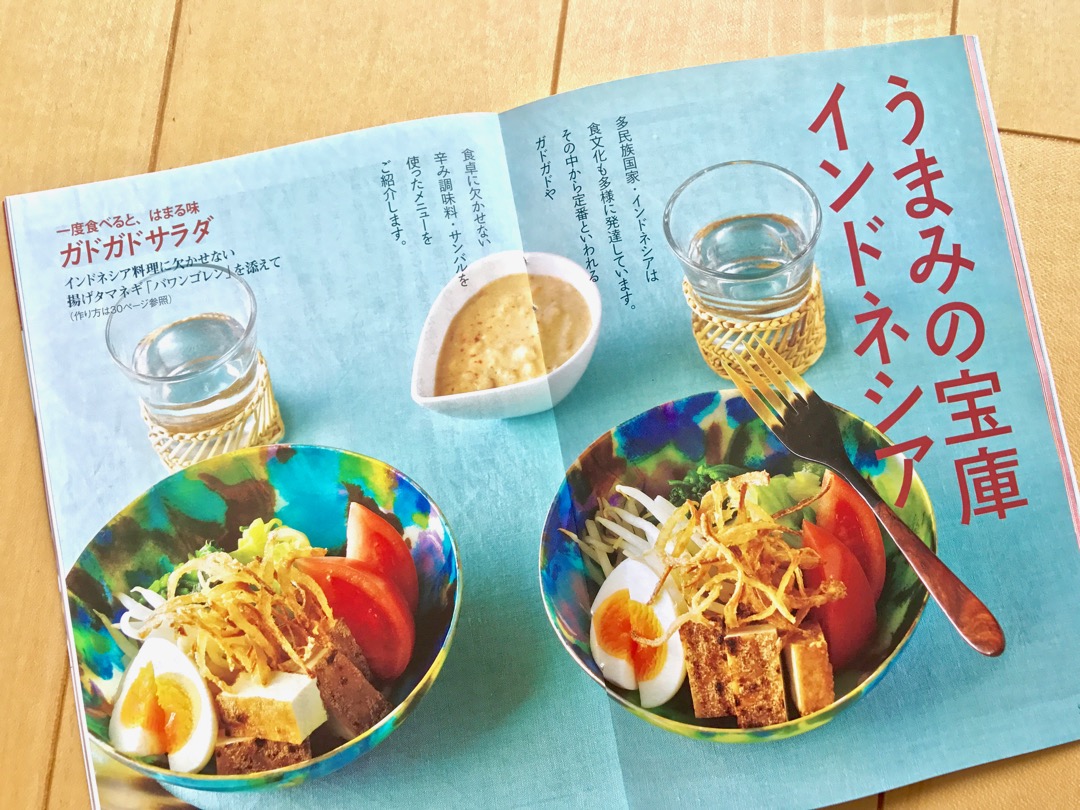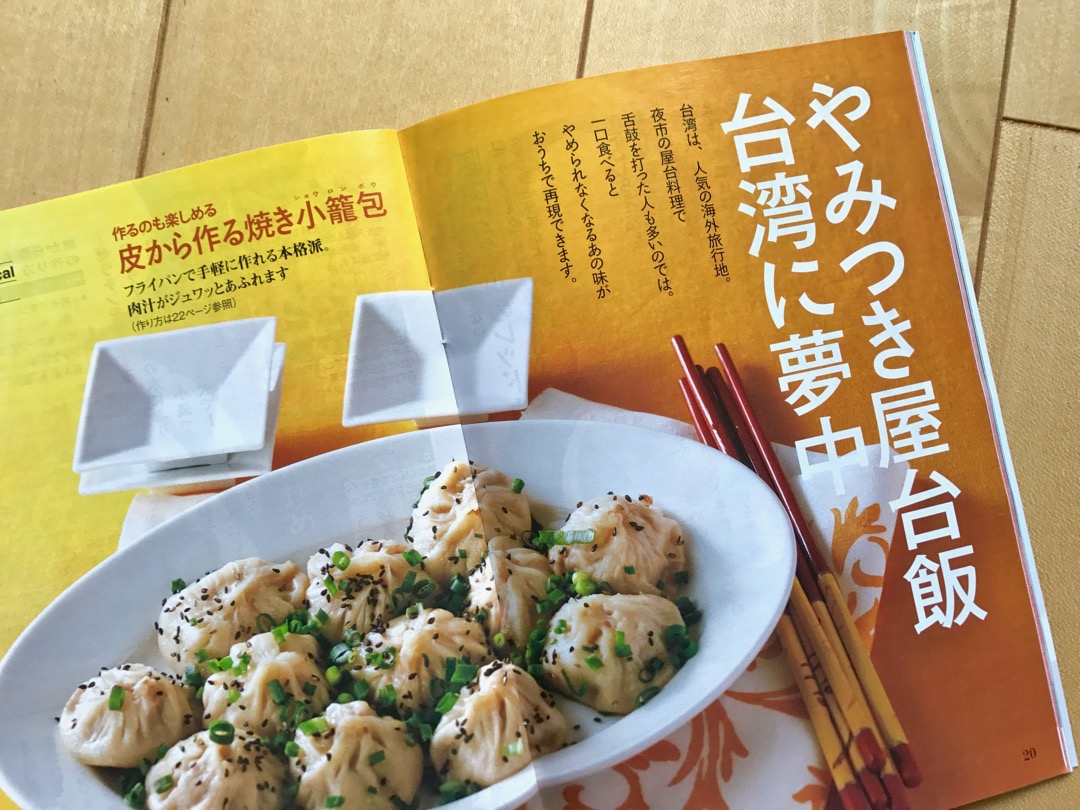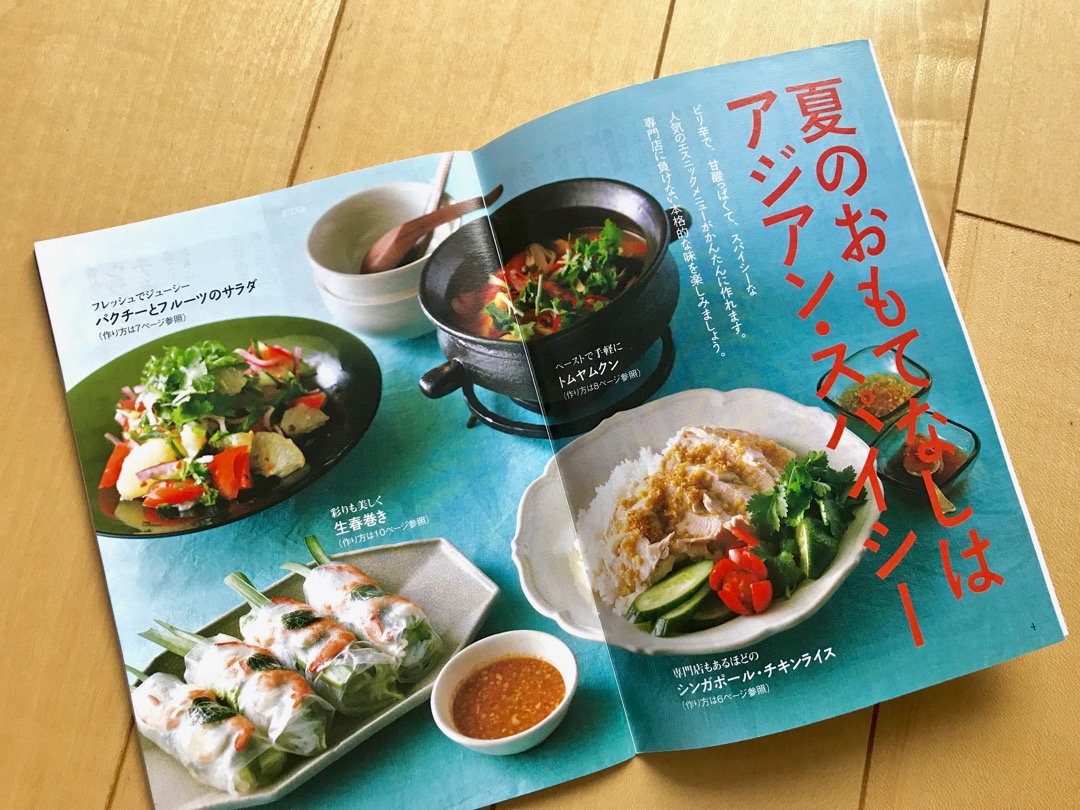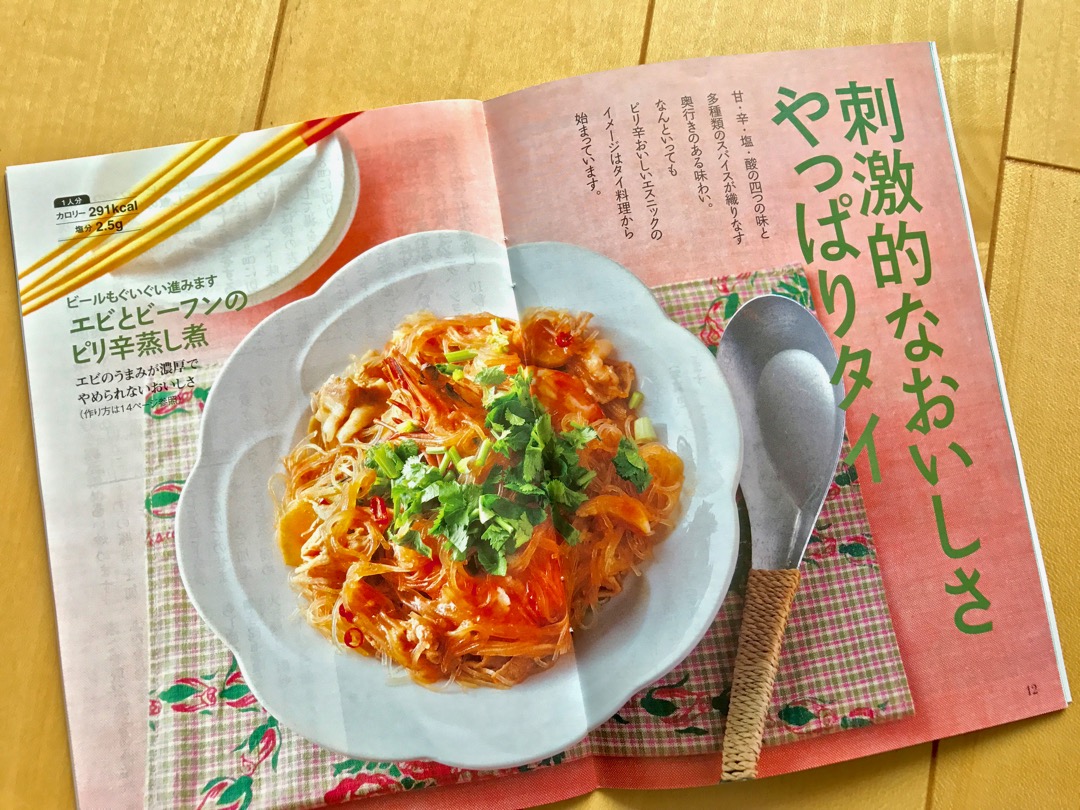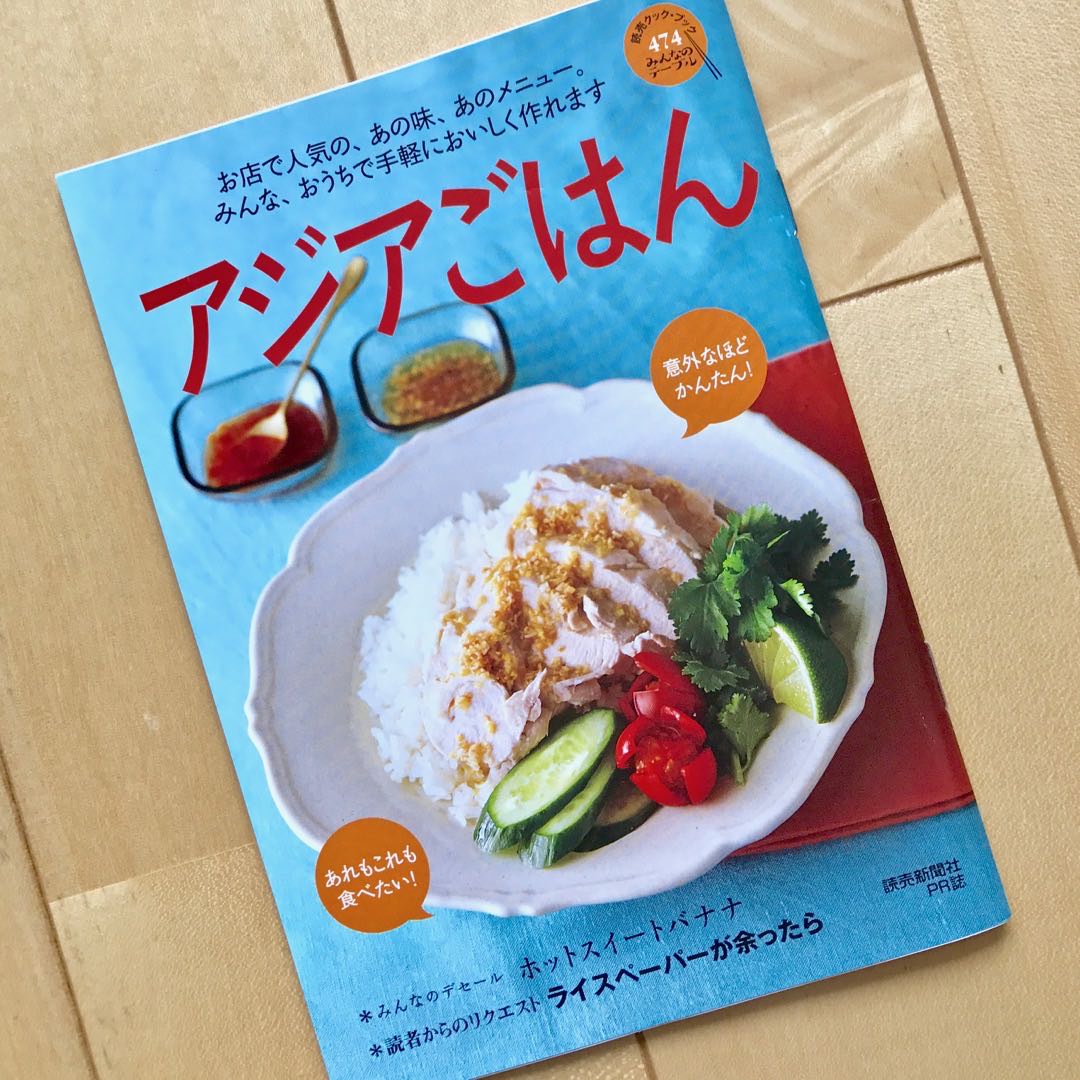
書名:せかいは新しくなる
著者:藤本四郎、日本聖書協会
発行:日本聖書協会
日本テレビ系の火曜サプライズ。
「心」の文字が小さく感じる…。
他社の漢字書体に合わせるのは難しいのだ。
会社によっては漢字の大きさが揃ってないこともあるから…。
いつもお世話になっています。「墨東ルイカ」制作中のミニコミ紙「演歌歌謡通信」のトップ記事の見出しで使わせてもらいました。
書名:だれか来る日に、便利なおかず
著者:ベターホーム協会
発行:ベターホーム出版局
同じシリーズ。
書名:作っておくと、便利なおかず
著者:ベターホーム協会
発行:ベターホーム出版局
書名:ガツめし関西版 2018-2019
発行:ぴあ
書店で見かけた墨東フォントの使用例です。
こういう食べ物の紹介にもピッタリですね。
太めのものは男っぽいですから、ピッタリですね。
首都圏版は違うデザイン(タイトルはわんぱく)でした…。
書名:魔法のスープ ボーンブロスでやせる
著者:鈴木功、鈴木睦美
発行:主婦の友社
書名:どうぶつしりとりえほん
著者:薮内正幸
発行:岩崎書店
書名:ツイン・ピークス読本
著者:滝本 誠
発行:河出書房新社
漫画雑誌内の予告ページ。
新聞社のPR誌。
本文中のタイトルにも…。